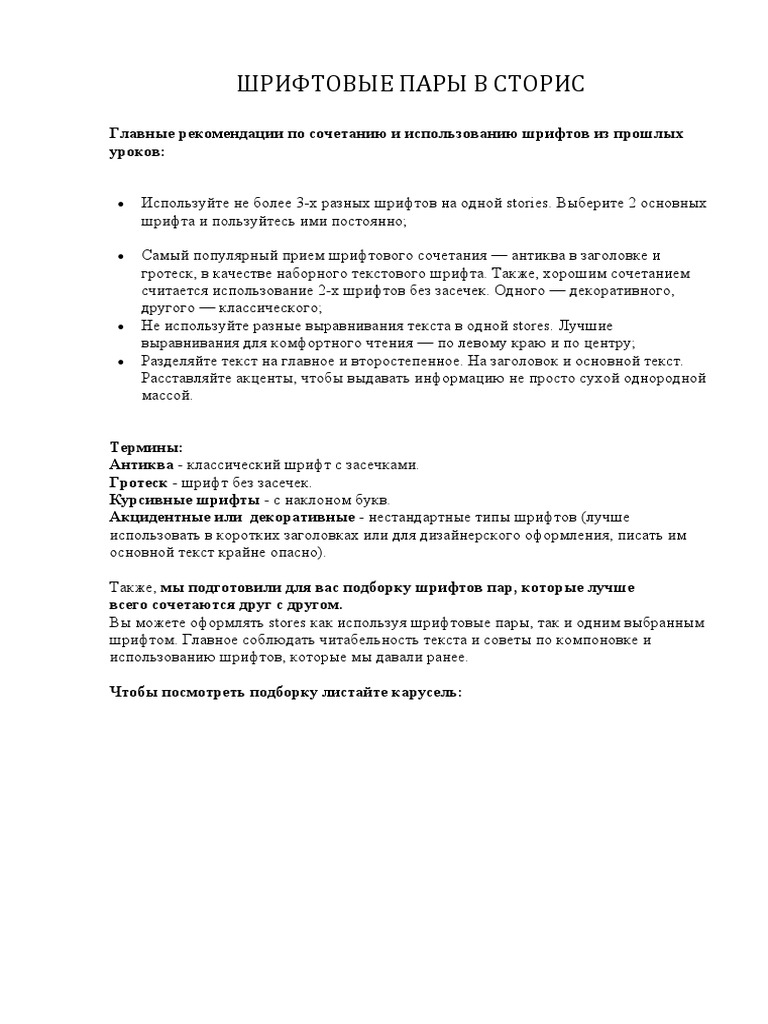
Правильный выбор шрифтов: секреты создания привлекательного дизайна
Шрифты являются важной составляющей веб-дизайна, поэтому выбрать подходящие шрифты - это ключ к созданию красивого и эффективного дизайна страницы. От правильного выбора шрифтов зависит впечатление, которое оставит ваш сайт на пользователях. В этой статье вы найдете полезные советы и идеи, как выбрать шрифты, которые добавят уникальность и стиль вашему дизайну.
Изучите основные типы шрифтов. Существуют различные типы шрифтов, такие как засечки, беззасечные, курсивные, гротески и другие. Изучите их особенности и применение, чтобы правильно выбирать шрифты для разных целей.
Сочетайте шрифты разного стиля и размера. Попробуйте комбинировать различные стили и размеры шрифтов, чтобы создать контраст и привлечь внимание к важным элементам на странице.
Учитывайте читабельность. Не забывайте о том, что ваш текст должен быть читабельным для пользователей. Избегайте слишком маленького размера шрифта и слишком сложных форм, которые могут затруднять чтение текста.